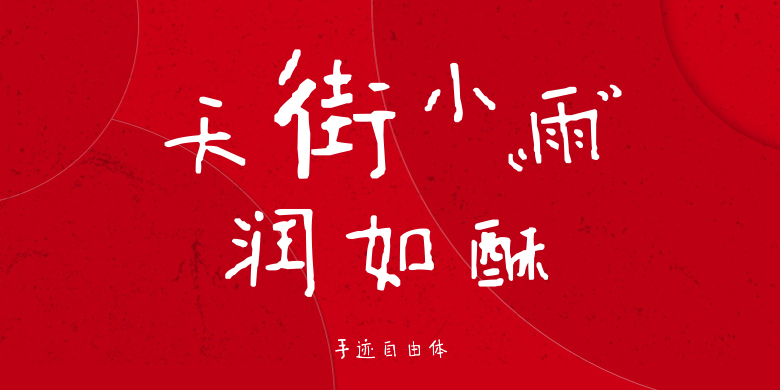
手迹自由体
手迹自由体,这款字体结构工整、笔画清晰,兼顾美观与易读性,适用于标题、正文、海报、包装、LOGO 等多种场景。字形优雅稳定,风格百搭耐看,适配日常排版与创意设计,让文字呈现更舒适、更具质感。手迹自由体一笔一画,皆是细节,以均衡的比例、流畅的线条打造舒适视觉体验,字形端正大气,风格简约现代。无论是商业设计、品牌宣传还是日常排版,都能轻松驾驭,让文字更有格调与力量。手迹自由体字体下载。